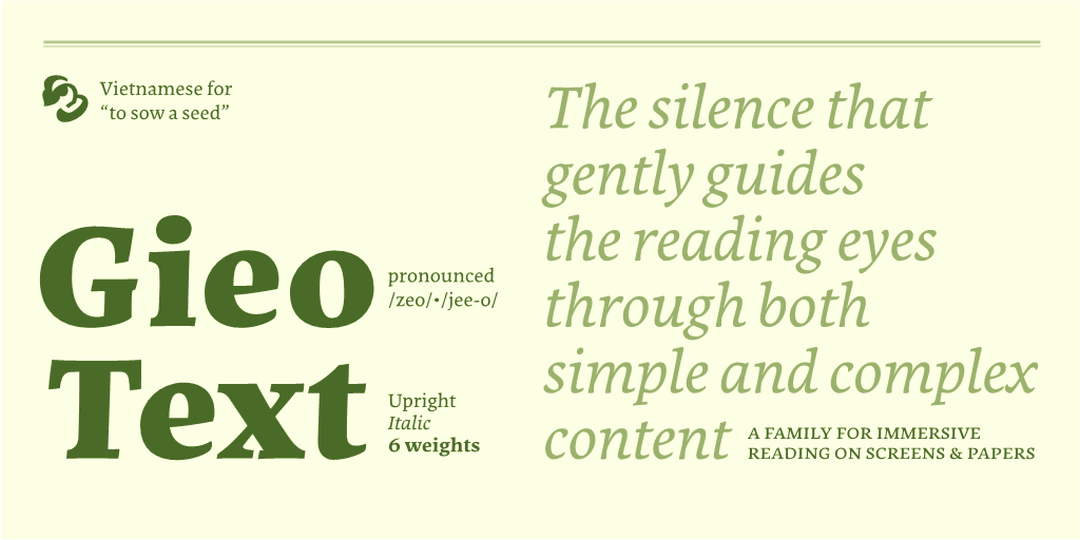
Gieo Text
クラシカルな正統派本文用オールドスタイルローマン。コントラストが弱く、ストロークも完全な直線ではなくわずかに曲がったような線を使い、アップライトも全体的にほんのり右に傾いており、目に優しく可読性に注意して設計されていることが伺える丁寧な書体。ブラケットが片方なかったりするところにちょっとした個性を感じるだろうか。ベトナム人の作者が数年前に英国のレディング大学で学んでいる際に製作を開始したらしい。名前の gieo はベトナム語で「種を蒔く」というような意味だそうだ。6ウェイト。